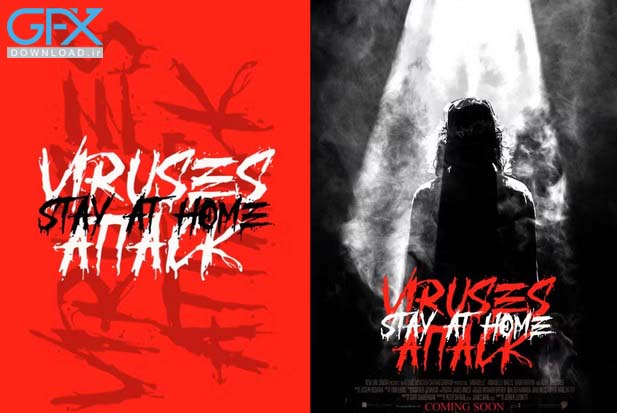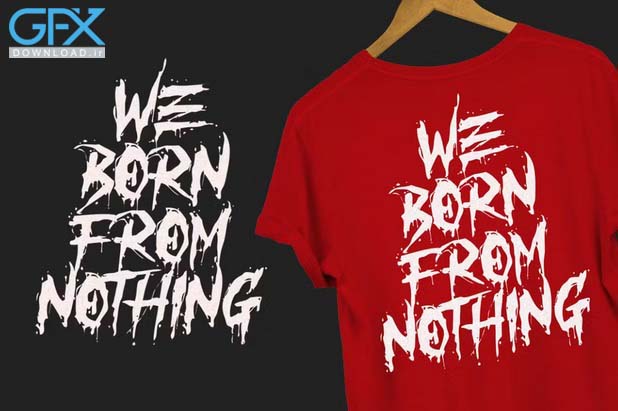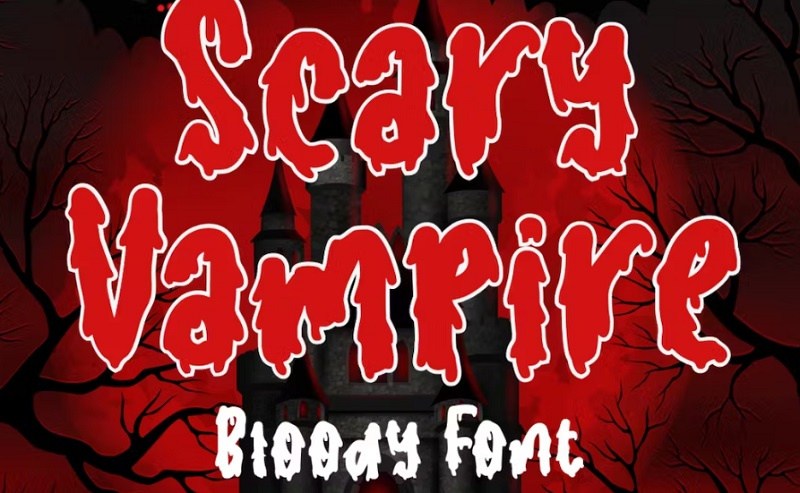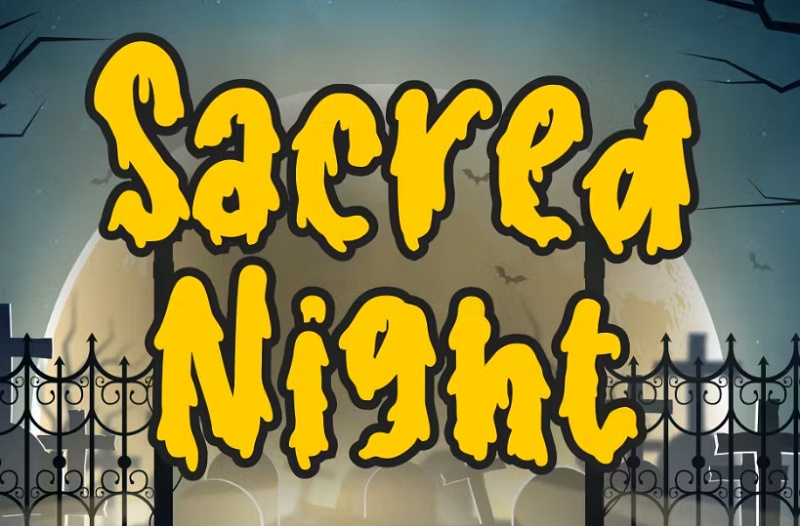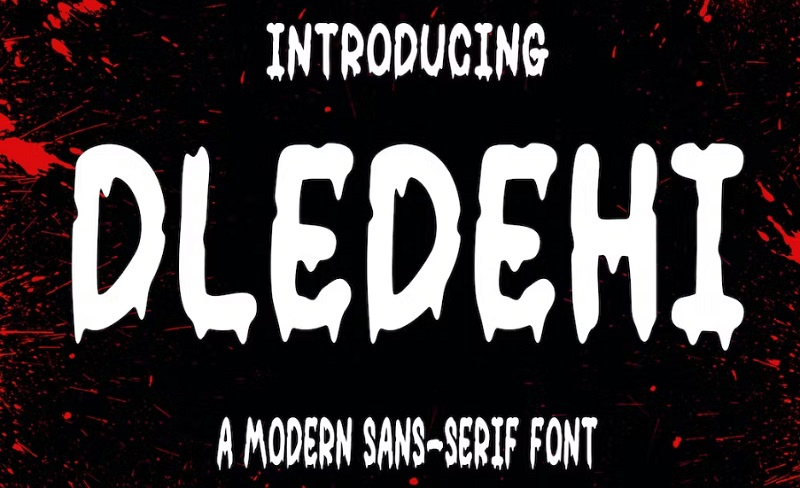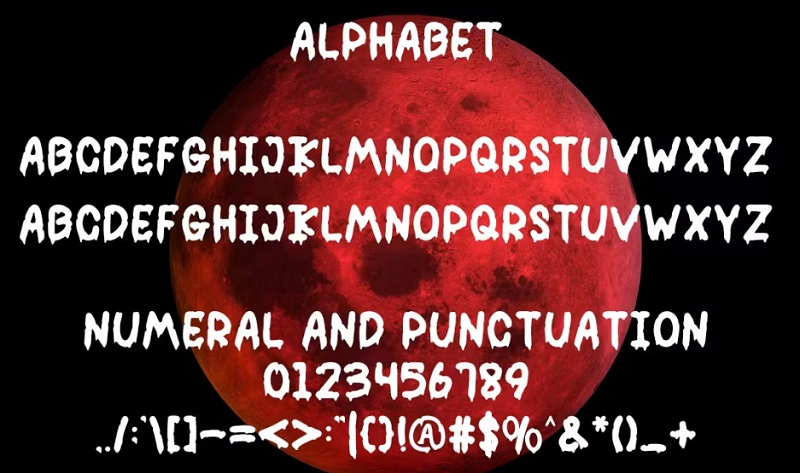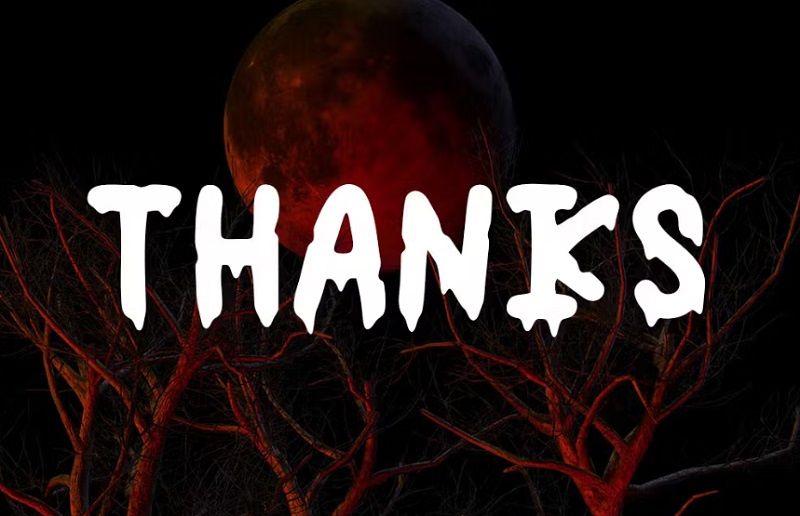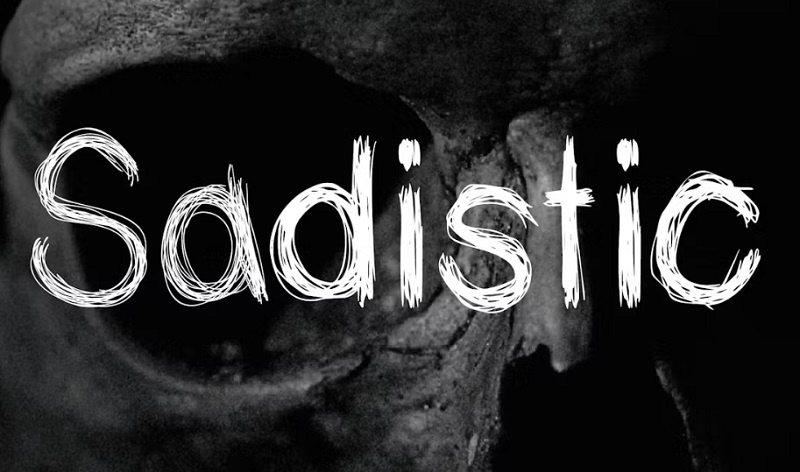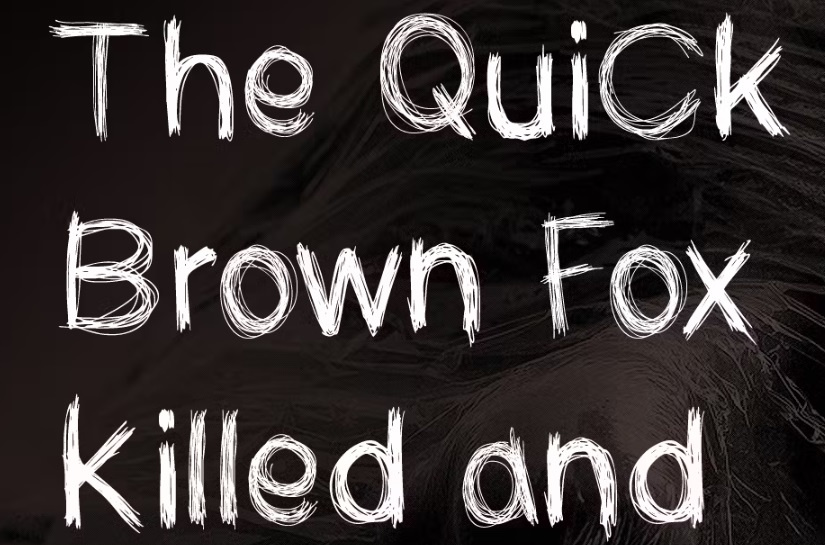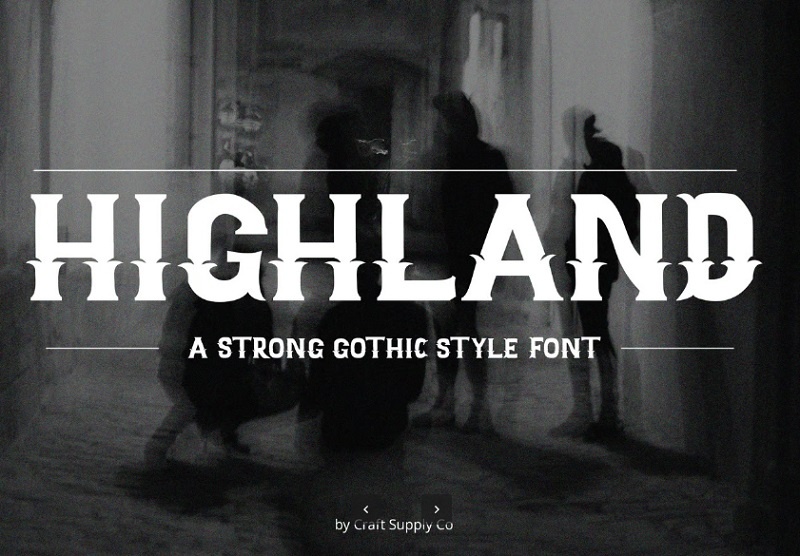
فونت ترسناک⭐بهترین فونت های انگلیسی ترسناک و رازآلود
دانلود فونت ترسناک Palikan
فونت انگلیسی ترسناک Palikan یک فونت سریف منحصر به فرد است که در قسمت بالا نازک و در پایین ضخیم است. این فونت انگلیسی برای ایجاد حالات ترسناک و دلهره آور ساخته شده است. ایده آل برای پوستر، فیلم، کتاب، جلد، مجلات و موارد دیگر. برای دانلود فونت ترسناک Palikan و پیش نمایش مجموعه به ادامه مطلب مراجعه کنید.
دانلود فونت انگلیسی ترسناک HOODVILLE
این فونت با تم تاریکی و وحشت و حس ترس می باشد. این فونت ترسناک HOODVILLE مناسب برای بازار کتاب با تم های شبح آور، پوستر بازی ترسناک، لوازم التحریر، فونت وسایل مدرسه، جلدهای یوتیوب، تصاویر کوچک یوتیوب، جلد صفحه رسانه های اجتماعی و غیره...مناسب است.
دانلود فونت انگلیسی ترسناک با طرح الکتریسیته Shock Block
ین فونت جذاب با طراحی چشم نوازی که با قلم و جوهر با دست طراحی شده است تا ظاهر کمیک های ترسناک کلاسیک، فیلم های دهه 80 و کارتون ها را تکرار کند، فونت ترسناک با طرح الکتریسیته Shock Block یک فونت بسیار زیبا است که توسط علوم تجربی و طرح الکتریسته و گیگاوات برق طراحی شده است! مناسب برای هشدار دادن به کاربر ، برای لزوم استفاده از عینک ایمنی!
دانلود فونت انگلیسی با طرح ترسناک Scarecrow
این فونت ترسناک و رازآلود با نام Scarecrow یکی از فونت های جدید و خلاقانه است که مناسب برای طراحی روی تی شرت پوستر لیبل و طراحی لوگو و … می باشد. این فونت از فیلم های ترسناک هالیوودی الهام گرفته شده است. این فونت با طراحی بی نظیر از جلوه های براش جوهری واقعی برای هر طرحی مناسب است مانند باند پوستر ، طراحی لباس ، طراحی محصول ، بسته بندی ، طراحی برچسب ، عنوان فیلم / فیلم ، نقل قول و غیره . با دانلود فونت ترسناک انگلیسی Scarecrow توجه بیننده را به خود جلب کنید همچنین شما می توانید برای ادیت بهترین عکس های ترسناک را در جی اف ایکس دانلود دریافت کنید.
دانلود فونت ترسناک و رازآلود برای فیلم و بازی
فونت ترسناک و راز آلود BLACK KNIGHT یکی از زیباترین و جدیدترین فونت های حرفه ای می باشد که طراحی بی نظیر و جذاب آن می تواند توجه بیننده را به خود جلب کند. دانلود فونت ترسناک و رازآلود کاملا مناسب بازی های رمز و راز و ترسناک ، هالووین، پوستر ، عنوان فیلم ، منوی فست فود ، مجله ، جلد یوتیوب ، تصاویر کوچک یوتیوب ، جلد صفحه رسانه های اجتماعی و غیره می باشد.
فونت ترسناک انگلیسی خون آشام Scary Vampire
Scary Vampire یک فونت انگلیسی ترسناک خونین است که با حروف بزرگ و کوچک، نمادهای چند زبانه، اعداد و علائم نگارشی همراه است. شامل فایل Otf، Ttf، Woff می باشد. مناسب بازی های رمز و راز و ترسناک ، هالووین، پوستر ، عنوان فیلم ، خون آشام و ...
دانلود فونت انگلیسی ترسناک Dledehi
فونت Dledehi یک فونت انگلیسی ترسناک و جذاب است. مناسب برای نیازهای حرفه ای و برندینگ محصول، نقل قول، لوگو، هدر وبلاگ، پوستر، نامه، دعوت نامه، لوازم التحریر و غیره است... اگر برای طراحی های خود به فونت انگلیسی ترسناک احتیاج دارید این فونت وحشتناک Dledehi را به شما پیشنهاد می کنیم.
فونت ترسناک و شیطانی انگلیسی Sadistic
فونت ترسناک و شیطانی انگلیسی با نام Sadistic یک فونت انگلیسی رسناک به سبک دست نویس می باشد. این فونت مناسب برای هالووین، طراحی های شیطانی ترسناک و ... است.
فونت انگلیسی ترسناک و وحشتناک
انتخاب فونت مناسب می‌تواند نقش مهمی در ایجاد جوی ترسناک و جذاب داشته باشد. اگر به دنبال فونت‌هایی هستید که به طرح‌هایتان حس وحشت و دلهره ببخشند این فونت ترسناک انگیسی با نام Highand مناسب طراحی های شما است.